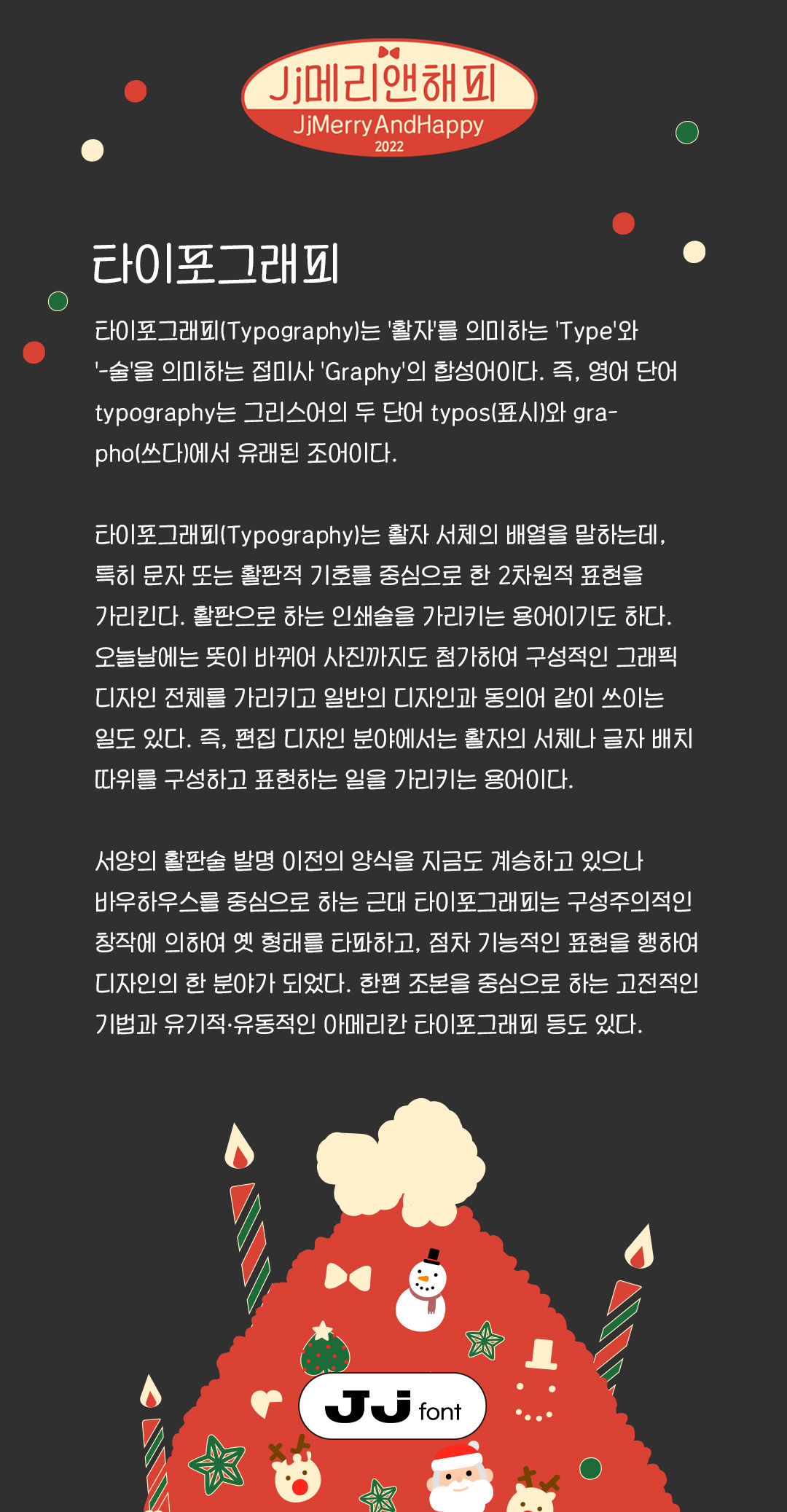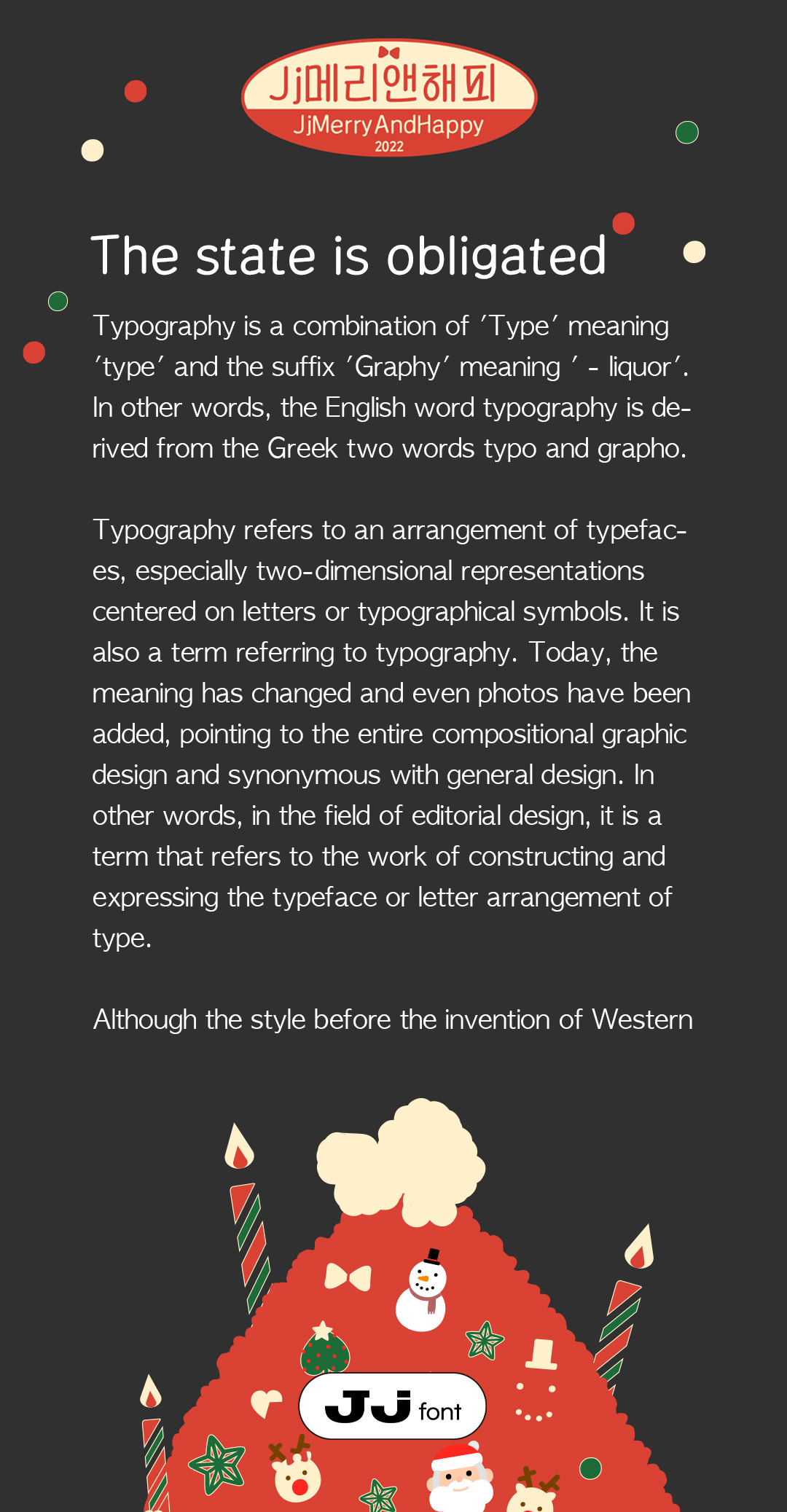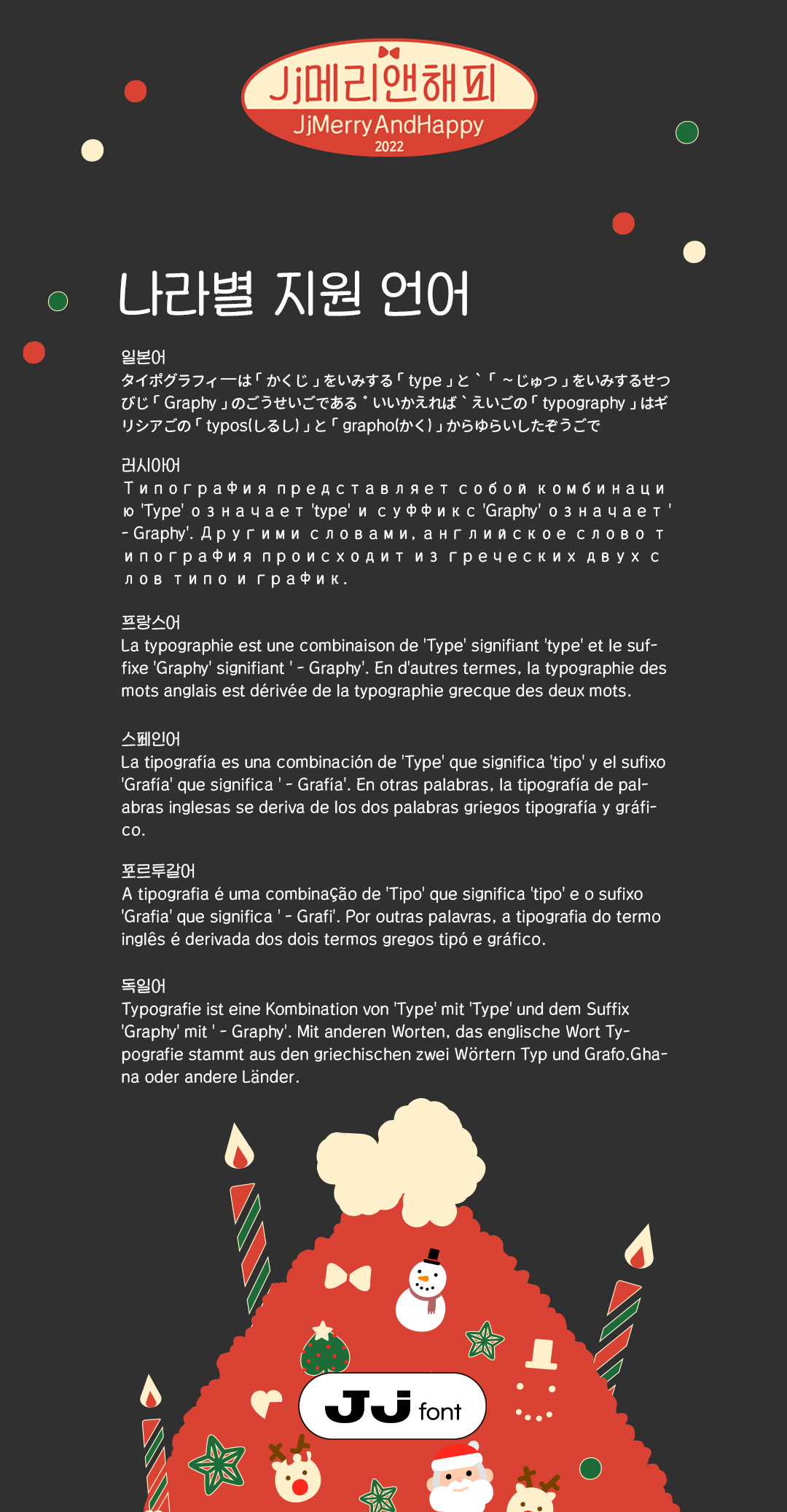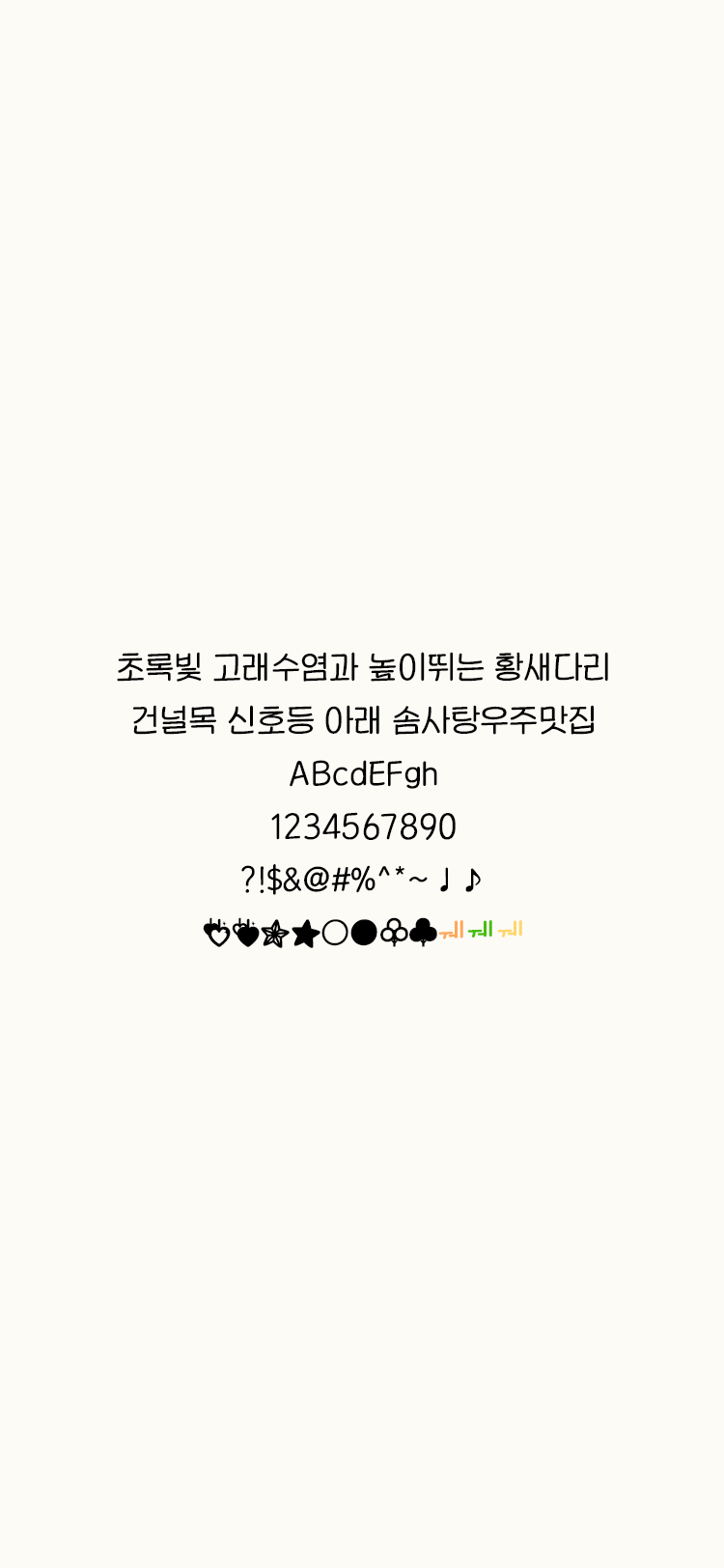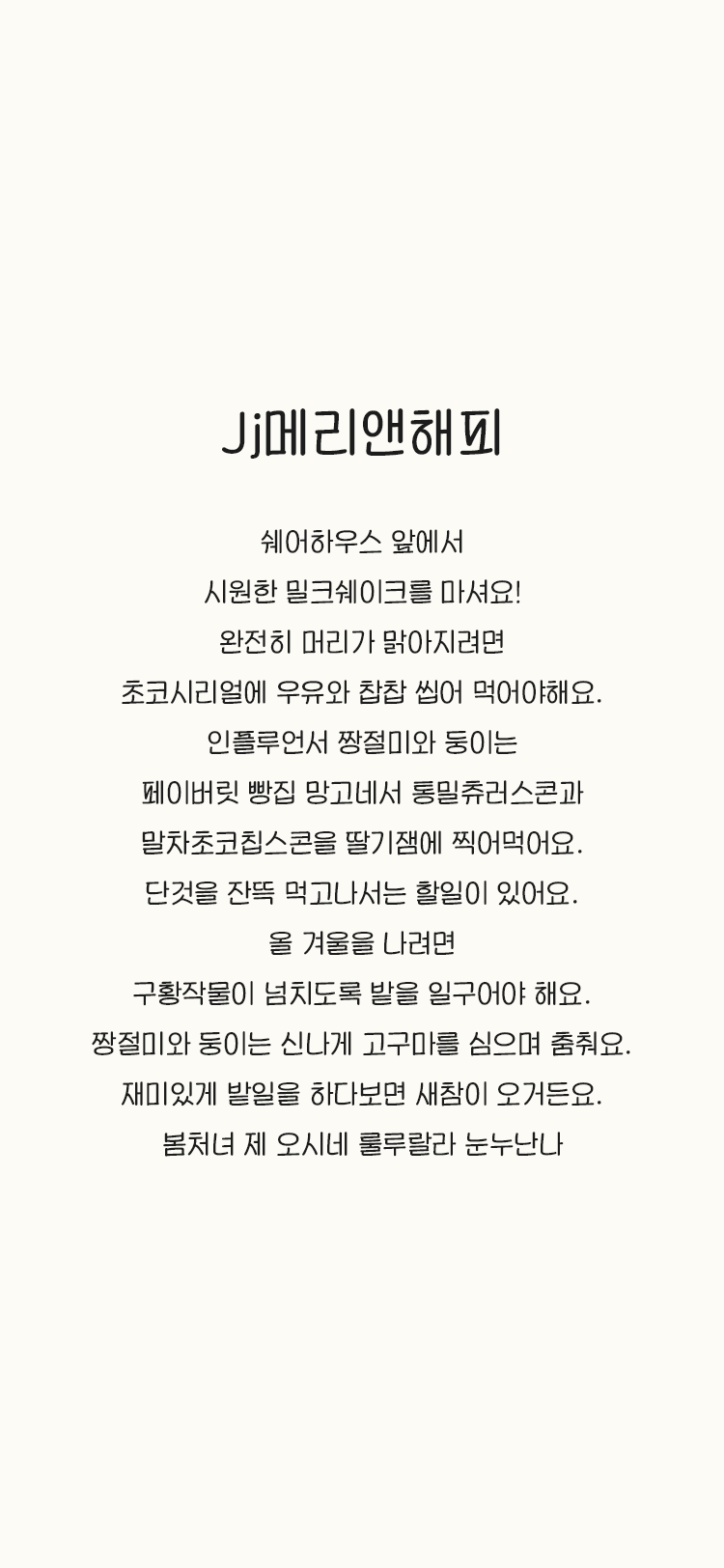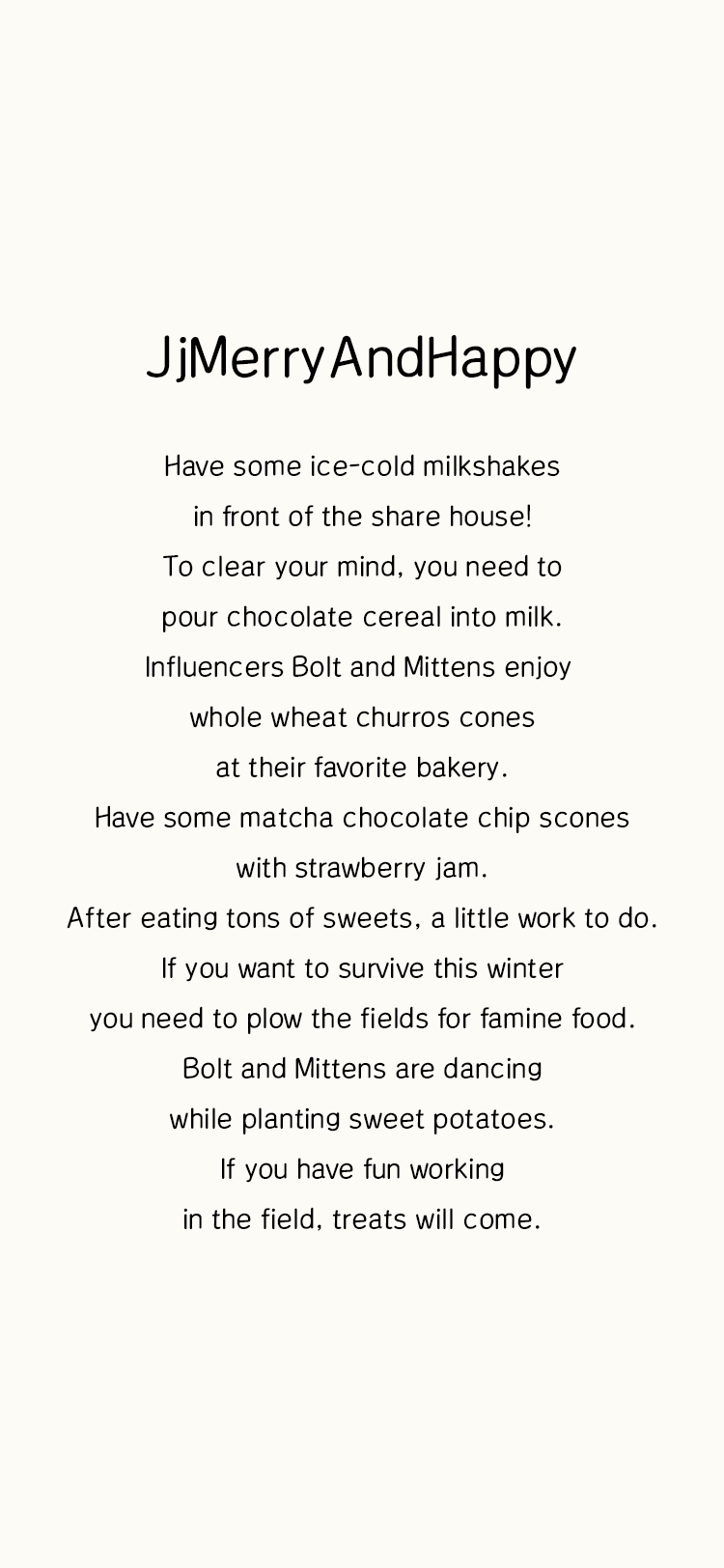
이제는 내 크리스마스도 Merry야 :)
New yearsms Happy야♥
Jj메리앤해피는 필기감의 디테일이 느껴지는 획으로 직선과 곡선이 조화로운 꽉찬네모를 안에 있는 손글씨 입니다.
- ;), ;>을 치면 귀여운 눈사람과 산타를 만날 수 있어요.
- ♂♀☆★♡♥♤♠♧♣☞☜에서 컬러 딩벳을 지원합니다.
- 라틴, 일본어(히라가나, 카타카나), 키릴문자를 지원합니다.